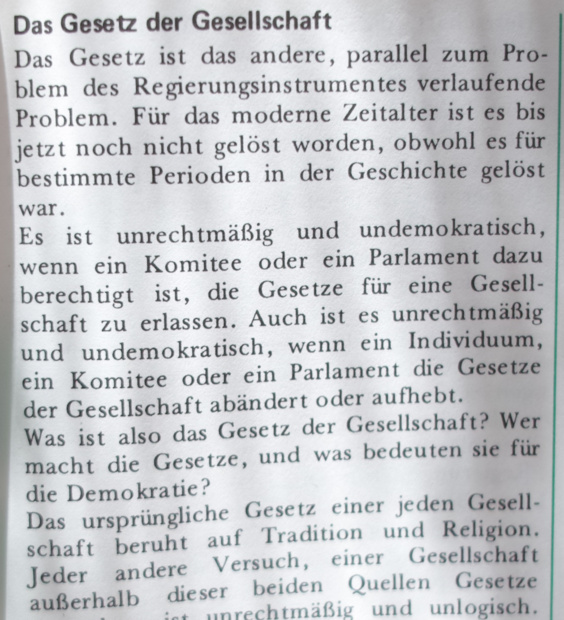
nun was einfacheres ...
Wer nicht von dreitausend Jahren
Sich weiß Rechenschaft zu geben,
Bleib im Dunkeln unerfahren,
Mag von Tag zu Tage leben.
Goethe
...nachdem ich kapiert habe dass ihr nicht mal über die letzten 100 Jahre könnt Rechenschaft ablegen... [euer Handwerk, Entschuldigung, KUNSThandwerk betreffend],
da ihr wahrscheinlich mit dem US-Imperial Font aus Micky Mouse und Donald Duck*) sozialisiert wurdet, hier etwas aus den letzten 30 Jahren.. Es muß sich wohl um etwas Baskerville-Ähnliches handeln...
Aber jetzt bitte nicht einwenden, Gaddafi hätte in den 80ern wohl seinen eigenen Font zur Herausgabe geschnitten, okay?
wer also kann mir helfen, jaja, exakt diesen Schnitt zu finden? *gggg*
P.S. *) wahrscheinlich kam von daher nie das Bedürfnis auf, sich mit den guten 'alten' deutschen Schriften zu befassen... weil ihr einfach keinen Bezug dazu hattet...
ich hab allein an die 50 Bücher gesetzt in ALDINE aus dem Zeitraum zwischen 1880-1910... alwas? dieser Aldine Schnitt hat natürlich nichts mit dem zu tun, was im Netz (unter euch Künstlern und Verkaufskünstlern) so unter diesem Namen läuft...
wann bringt endlich mal jemand den Anstand auf, die Sachen 1 zu 1 zu kopieren, ohne seinen im Grunde eh bloß reaktionären Senf dazuzugeben????
ich bin nicht mal Befürworter dieses Aldine fonts.. da selbst mir als eher proportionsblindem Menschen die Defizite im Schriftbild zur Prillwitz einleuchten...
Und dennoch muß es wohl der beste Universalfont dieser Zeit gewesen sein.....
jedem kollegen, der zu einem derart unscharfen foto/scan mit bestimmtheit mehr sagen kann als das bereits von dir selbst vermutete, also ›eine baskerville‹, ist mein respekt gewiss.
dieser Aldine Schnitt hat natürlich nichts mit dem zu tun, was im Netz (unter euch Künstlern und Verkaufskünstlern) so unter diesem Namen läuft
bin zwar weder künstler noch verkaufskünstler, doch aldinen sind mir aus einer ganz anderen zeit, zu der auch dein zitat besser passen würde, ein begriff, auch wenn ich der garamondschen tradition gefühlsmäßig den vorzug gebe. dann kenne ich ein softwarehaus dieses namens, ein konkurrent zu adobe und von denen afair übernommen. oder möchtest du nur damit protzen, dass du den alterthümlichen (sic) begriff aldine statt des gebräuchlicheren antiqua kennst?
was genau möchtest du mit deinem trolligen verhalten denn erreichen?
Das hab ich mich auch grad gefragt. Ich glaube, es ist einfach der Umnachtung (2:35 Uhr) und vielleicht der Einnahme bewusstseinsbelustigender Substanzen (ein guter Drink) geschuldet.
Da ist der untere Schwung beim g zu dünn.
Ich werfe mal Berthold Baskerville Book BQ (und weil der genau Schnitte erwünscht ist: Regular) in die Runde.
Okay, das Q passt auch nicht :-(
bin zwar weder künstler noch verkaufskünstler, doch aldinen sind mir aus einer ganz anderen zeit, zu der auch dein zitat besser passen würde, ein begriff, auch wenn ich der garamondschen tradition gefühlsmäßig den vorzug gebe. dann kenne ich ein softwarehaus dieses namens, ein konkurrent zu adobe und von denen afair übernommen. oder möchtest du nur damit protzen, dass du den alterthümlichen (sic) begriff aldine statt des gebräuchlicheren antiqua kennst?
was genau möchtest du mit deinem trolligen verhalten denn erreichen?
Ach herrje! vielen Dank erstmal für die Hinweis auf mein 'Aldine' Geprotze.
Somit begreif ich nun daß ich umsonst Aldine in eines meiner Bücher schrieb..
Denn ich ging davon aus, daß im Katechsimus der Buchdruckkunst S.99 die Namen der Schnitte dabeistünde ;-)
ich lese also Romansich von Schelter & Giesecke.. scrolle nach oben wobei ich nur auf den Eindruck der Schriften achte...
und komm auf eine mir bekannte.... wo Aldine dabei steht..
was soll ich mir jetzt als Antitypograf und Antikünstler dabei denken?
und nun überkommen mich gleich wieder Schmerzen, wenn ich daran denke, daß dieser spezielle Font den ich suche EBEN NICHT Aldine heißt, und man wieder vor der leidigen Tatsache steht, allein auf weiter Flur zu stehen..
Denn das 7 Ärzte 7 Diagnosen Spiel spielt es hier scheinbar mit Schnitten. Wo keiner exakt anzugeben versteht WAS den nun vor der Hand liegt.
@das ach so trolligem Verhalten:
gesetzt du hättest ein 300 Jahre altes Mathebuch zu setzen, an dem eine Zeile halb fiehle... mit unbekannten und heute ungebräuchlichen Symbolen.... und du liefest von einem Mathematiker heutiger Denkschule zum nächsten um die exakte Form in Erfahrung zu bringen...
und keiner könnte dir auch nur irgendwie weiterhelfen, sondern lediglich mit (selbst für dich als Nichtmathematiker nachvollziehbaren) dämlichen Allgemeinplätzen daherkommen... diese dann aber noch mit super frech wie dämlichen Beisatz wie 'nimm doch ein anderes Buch, muß ja nicht exakt dasselbe sein' enden zu lassen...
insofern wär ich über sachdienlichen hinweis immer noch dankbar...
Ich habe eine sehr starke Vermutung, was wir auf Deinem Foto sehen können, aber nach Deinem Auftritt hier halte ich mich einfach mal vornehm zurück – und kann mir somit auch nicht den Respekt des Kollegen ThierryM verdienen – zumal es sich um was »US-Imperialistisches« handelt. Das nur als kleiner Hinweis, daß »wir« hier nicht so blöd sind, wie Du vielleicht glaubst.
lieber jens.... das freut mich zu hören!
ich schöpfe fast schon wieder hoffnung ;-)